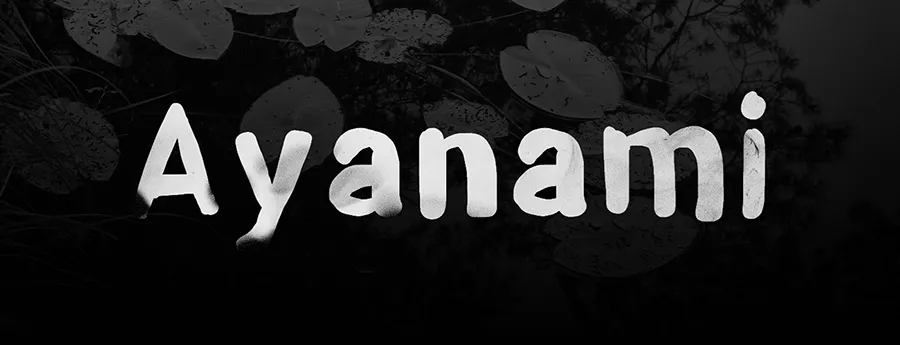
A Ayanami Font é uma opção divertida e versátil para adicionar um toque especial aos seus projetos digitais. Inspirada na personagem fictícia Rei Ayanami, de Neon Genesis Evangelion, esta fonte é perfeita para personalizar mensagens ou adicionar graciosidade a qualquer projeto. Desenvolvida pelo designer Hamilton, ela tem uma aparência fresca e divertida, parecendo desenhada com um pincel da filbert, que adiciona uma personalidade descontraída aos textos. Não é apenas uma fonte útil para usar em seus projetos de design gráfico, mas também uma maneira criativa de incorporar a cultura pop na sua paleta de recursos. Hamilton, nosso designer, deseja-lhe muita inspiração e bom trabalho ao experimentar esta divertida nova opção na família da Ayanami Font. E não se esqueça, visite o portfólio do próprio designer para explorar mais fontes incríveis.